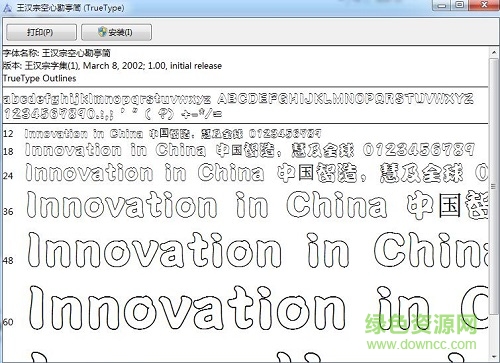
王漢宗空心勘亭流字體
王漢宗空心勘亭簡(jiǎn)是一款王漢宗根據(jù)勘亭流體打造的藝術(shù)字體,該字體不僅延續(xù)了勘亭流體的所有特色,還采用空心的方式,讓字體更加充滿藝術(shù)性,有需要的朋友歡迎下載!
王漢宗空心勘亭簡(jiǎn)簡(jiǎn)介
王漢宗空心勘亭簡(jiǎn)是一款空心的勘亭流體字體,字體筆畫中極少出現(xiàn)直線與折角,幾乎全由曲線和彎角構(gòu)成,形成了其特有的藝術(shù)效果,被廣泛應(yīng)用于表現(xiàn)日式風(fēng)格的招牌、標(biāo)題、包裝等上面,倍受廣大平面設(shè)計(jì)者的青睞。
王漢宗空心勘亭簡(jiǎn)